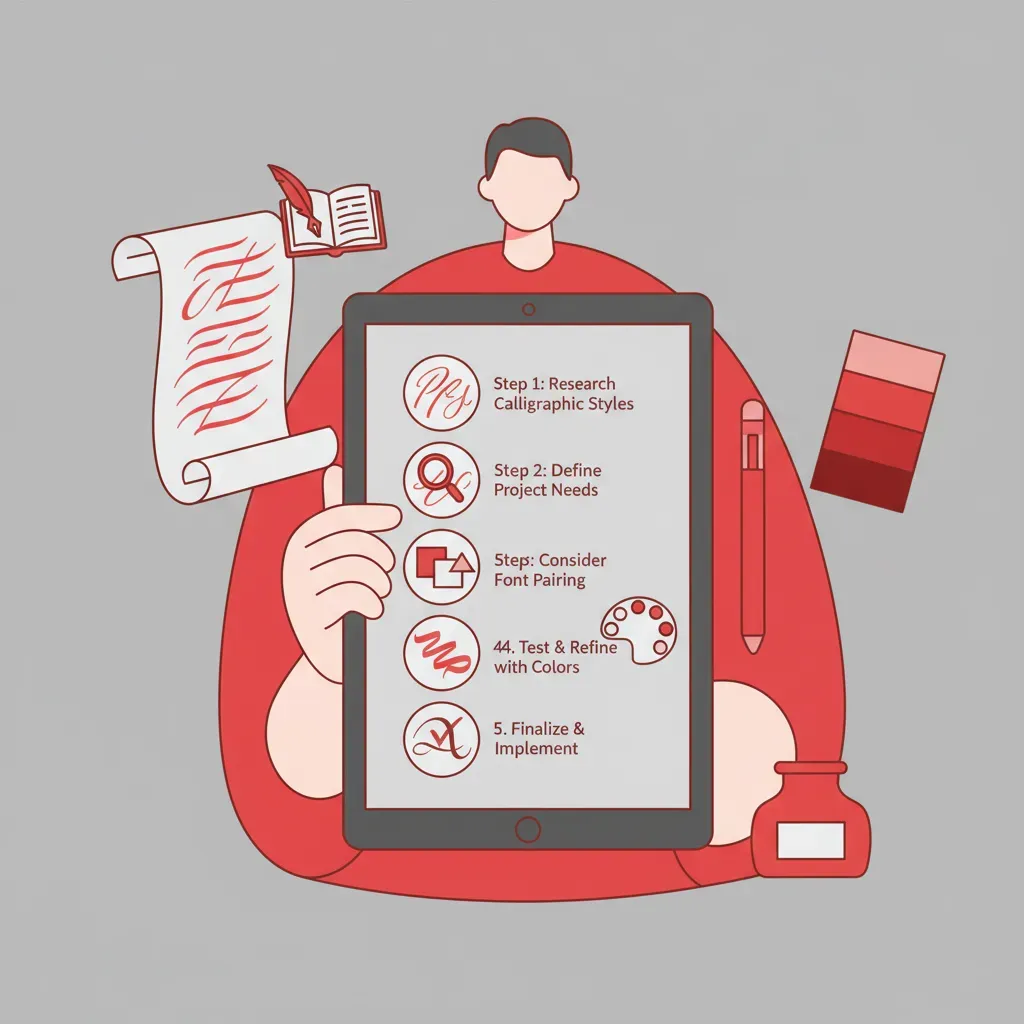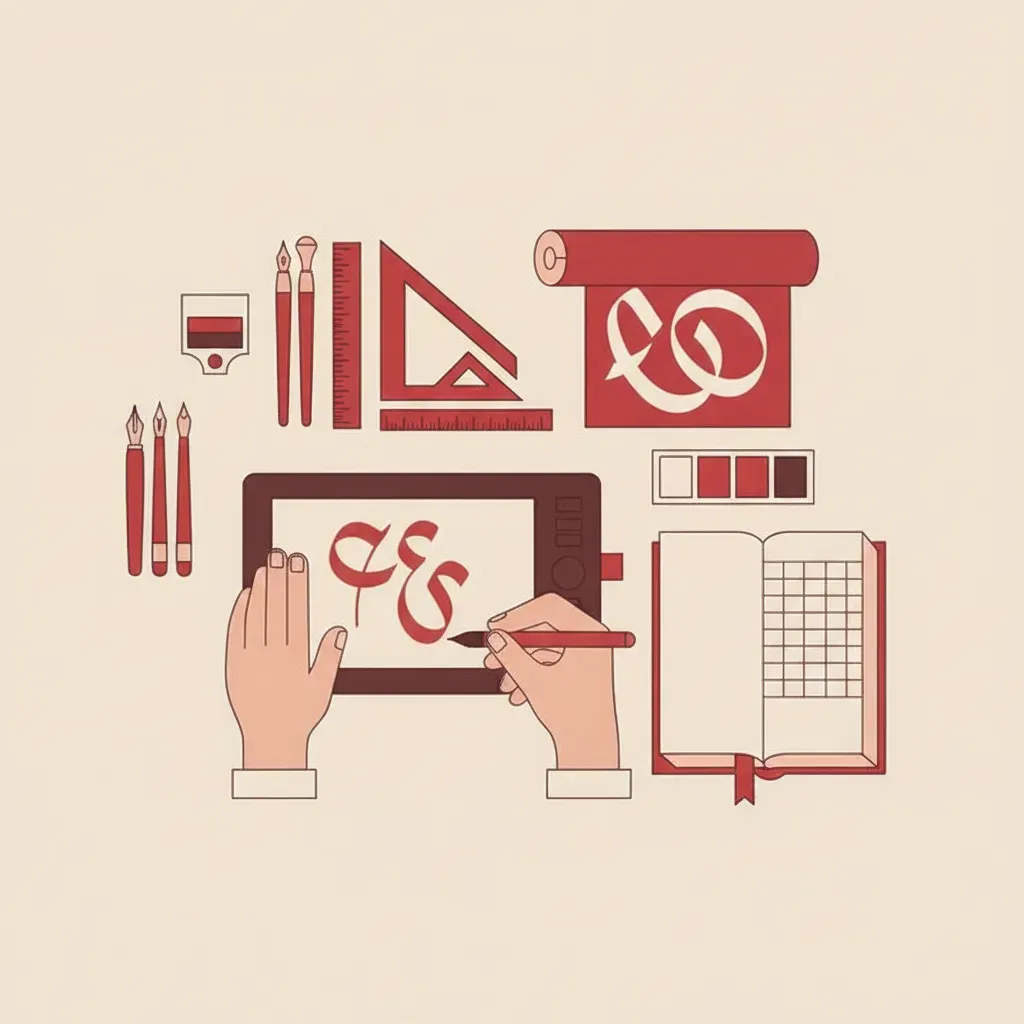
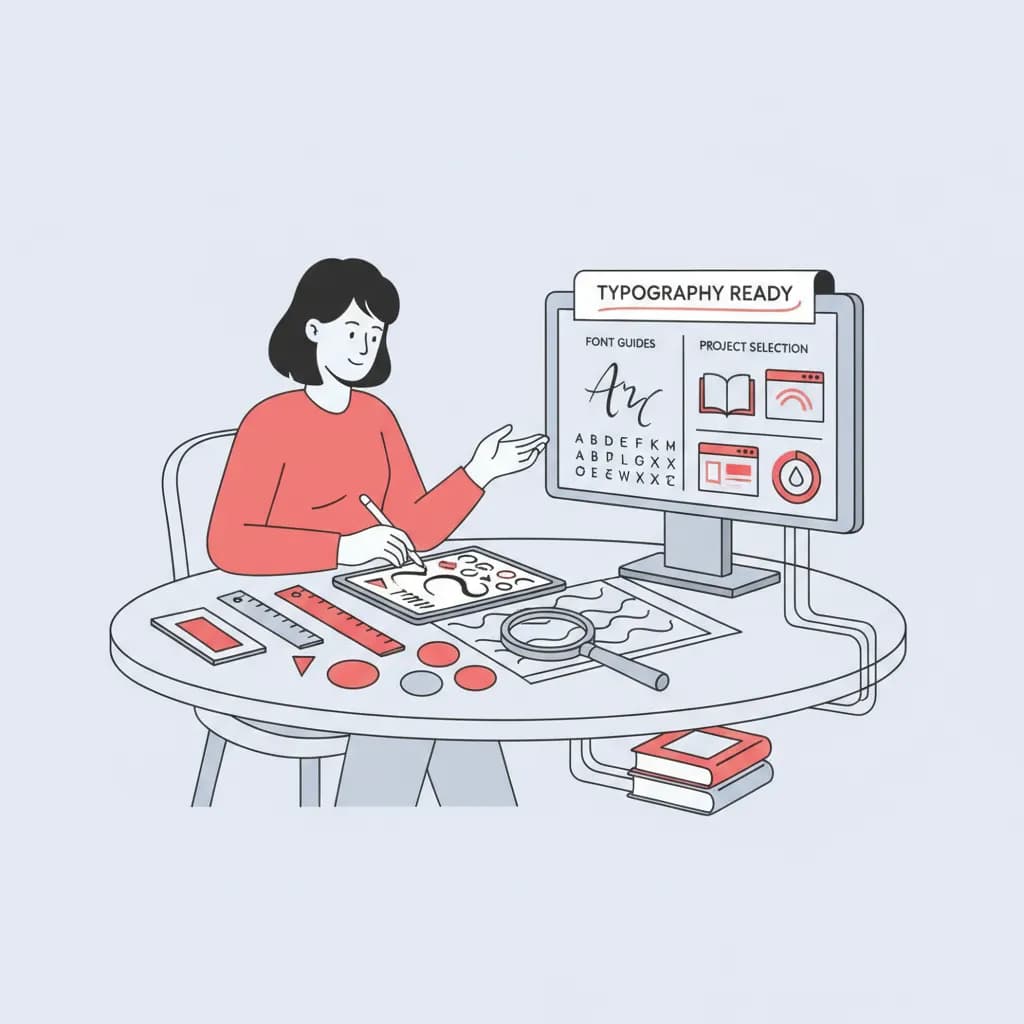
טיפוגרפיה היא לא רק עניין של אסתטיקה – היא שפה שמדברת לפני שהקורא קרא מילה אחת. הדרכות פונטים הן הדרך המהירה ביותר להבין איך הגופן שבחרתם משפיע על תפיסת המסר, על קריאות הטקסט ועל האופן שבו הלקוח חווה את המותג שלכם. בין אם אתם מעצבים גרפיים מנוסים ובין אם אתם בעלי עסקים שרוצים לשדרג את הנוכחות הוויזואלית שלהם, הבנת עולם הטיפוגרפיה העברית היא כישור שמשתלם לאורך שנים. מאמר זה ריכז עבורכם את העקרונות המרכזיים, הטיפים המעשיים ואת הטעויות הנפוצות שכדאי להכיר.
הדרכות פונטים שישדרגו את הטיפוגרפיה העברית שלכם
גופן עברי הוא מערכת סימנים בעלת אופי, ריתמוס ומשקל – לא רק קבוצת אותיות. כל גופן נושא בתוכו אסוציאציות שמשפיעות על הקורא ברמה שאינה מודעת. גופן עם קווים כבדים ואנכיים משדר יציבות ומקצועיות, בעוד גופן עם קווים זורמים וקישוטיים מעורר תחושות של חגיגיות ואלגנטיות. ההבנה של הרובד הזה היא הבסיס לכל עיצוב טיפוגרפי מוצלח.
בעברית קיימות מספר משפחות גופנים עיקריות שכדאי להכיר:
ההיכרות עם קטגוריות אלו היא נקודת הפתיחה לכל תהליך בחירת גופן. כשיודעים מה כל משפחה מעבירה, הבחירה הופכת מהחלטה אינטואיטיבית להחלטה מושכלת. ניתן לקרוא עוד על עקרונות טיפוגרפיה בוויקיפדיה.
בחירת גופן היא תהליך שיטתי, לא ניחוש. מעצבים מנוסים עוברים שלבים מוגדרים שמצמצמים את מרחב הבחירה ומובילים להחלטה נכונה:
שלב 1: הגדרת אופי המותג
לפני שפותחים ספריית גופנים, שואלים: מה הרגש שהמותג רוצה להעביר? רשמי ומקצועי? חמים ואישי? חדשני ונועז? התשובה מצמצמת מיד את האפשרויות לקבוצה מוגדרת.
שלב 2: זיהוי מדיום השימוש
גופן שעובד מצוין על מסך עלול להיכשל בדפוס ולהיפך. גופנים לווב דורשים קריאות במסכים קטנים ועם רזולוציות שונות. גופנים לדפוס יכולים להיות מעודנים יותר.
שלב 3: בדיקת קריאות בגדלים שונים
בדקו את הגופן בגודל 10pt, 16pt ו-36pt. גופן מוצלח שומר על קריאות ועל אופיו בכל הגדלים. גופן שנראה טוב רק בגדלים גדולים אינו גמיש מספיק לשימוש כולל.
שלב 4: בחינת זוגות גופנים
רוב הפרויקטים משתמשים בשני גופנים – אחד לכותרות ואחד לטקסט גוף. הם צריכים להשלים זה את זה מבלי להתחרות. כלל מנחה: שלבו גופן סריף עם סנס-סריף, או גופן כבד עם גופן קל. ראו את המדריך המלא להתאמת פונטים לדוגמאות מפורטות.
גופן טוב הוא תנאי הכרחי אבל לא מספיק. הטיפוגרפיה היא מערכת שלמה שכוללת גם מרווחים, היררכיה ויזואלית ועקביות. הנה הטיפים שמעצבים מנוסים מיישמים בפרקטיקה:
כשמדובר בגופנים לכותרות, כדאי לשקול גופנים בעלי אופי חזק שמייצרים נוכחות ויזואלית. לדוגמה, פונט מנדולינה הוא גופן עם נוכחות חזקה המשלב אלגנטיות מובנית עם תנועה מודרנית – מתאים במיוחד לכותרות שצריכות לתפוס תשומת לב. ניתן לחקור יותר אפשרויות גופנים גם דרך Google Fonts שמציע מבחר גופנים עבריים בחינם.
אחד הנושאים המרכזיים שעולים בהדרכות פונטים הוא הטעויות שמעצבים חוזרים עליהן שוב ושוב. זיהוי הטעויות הנפוצות הוא צעד קריטי לשיפור מיידי של איכות העיצוב:
טעות 1: שימוש בגופן לא מנוקד בהקשר שדורש ניקוד
בהדרכות פונטים לעיצוב הזמנות ומסמכים דתיים, הטעות הנפוצה היא לבחור גופן שאינו תומך בניקוד ואז לגלות את הבעיה בשלב מאוחר. בדקו תמיד שהגופן שבחרתם תומך בניקוד מלא אם הפרויקט דורש זאת.
טעות 2: שימוש בגופן כתב יד לטקסט ארוך
גופנים קליגרפיים ואלגנטיים כמו גופני סקריפט מיועדים לכותרות, לוגואים ומשפטים קצרים. שימוש בהם לפסקאות ארוכות גורם לעייפות קריאה מהירה. בהדרכות פונטים, נושא זה מוזכר כמעט תמיד כאחת הטעויות הנפוצות ביותר.
טעות 4: שילוב גופנים שמתחרים זה בזה
שילוב שני גופנים דומים מדי יוצר בלבול – הקורא לא מבין מדוע יש שינוי. שילוב גופנים שונים מדי יוצר חוסר עקביות. הדרך הנכונה היא לשלב גופנים שמשלימים זה את זה מבחינת אופי ומשקל.
לכל סוג פרויקט יש דרישות טיפוגרפיות שונות. הכרת ההתאמות הנכונות מקצרת את זמן הבחירה ומשפרת את התוצאה הסופית:
סוג פרויקט סגנון גופן מומלץ דגשים מרכזיים הזמנות חתונה סקריפט קליגרפי אלגנטיות, רגש, תמיכה בניקוד אתר עסקי סנס-סריף נקי קריאות, מהירות טעינה, רישיון ווב לוגו מותג גופן ייחודי עם אופי בולטות, ייחודיות, זיכרון חומרי שיווק מודפסים סריף קלאסי קריאות בדפוס, רישיון דסקטופ רשתות חברתיות גופן בולד ודינמי בולטות בפיד, קריאות במובייללפרויקטים של מיתוג אירועים, פונט הינומה הוא דוגמה מצוינת לגופן קליגרפי עכשווי שמתאים לחתונות ואירועים פורמליים. הוא משלב נגיעות קליגרפיות עם מינימליזם מודרני, מה שמאפשר שימוש גמיש בהזמנות, בתפריטים ובחומרי עיצוב נלווים.
גופן לכותרות מיועד להופיע בגדלים גדולים ולהעביר אופי חזק – הוא יכול להיות מורכב, קישוטי ובולט. גופן לטקסט גוף חייב לשמור על קריאות בגדלים קטנים לאורך פסקאות ארוכות, ולכן הוא בדרך כלל נקי ופשוט יותר. שימוש בגופן כותרות לטקסט ארוך הוא אחת הטעויות הנפוצות שעולות בכל הדרכות הפונטים המקצועיות.
הכלל המקצועי הוא לא יותר משני גופנים בפרויקט אחד – גופן אחד לכותרות וגופן אחד לטקסט גוף. במקרים מיוחדים ניתן להוסיף גופן שלישי לאלמנטים ספציפיים כמו ציטוטים, אך זה דורש ניסיון ועין עיצובית מפותחת. שימוש ביותר מכך יוצר בדרך כלל חוסר עקביות ויזואלית.
הדרכות פונטים מעשיות מלמדות שהגופן הנכון אינו בהכרח הגופן הנאה ביותר – הוא הגופן שמשרת את המסר בצורה הטובה ביותר. כדי להמשיך ולהעמיק בנושא, כדאי לחקור את פונט כותרות ולהבין כיצד גופני כותרות עבריים יכולים לחזק כל שורה בעיצוב.